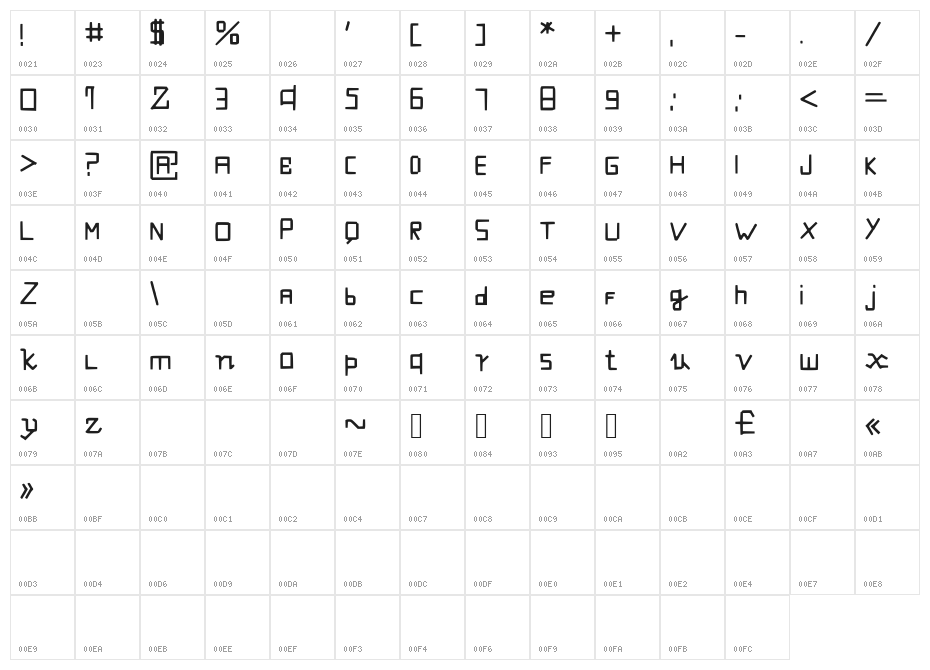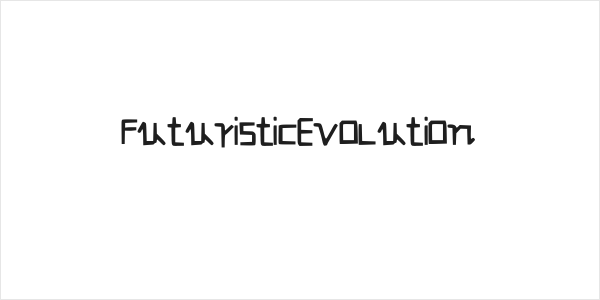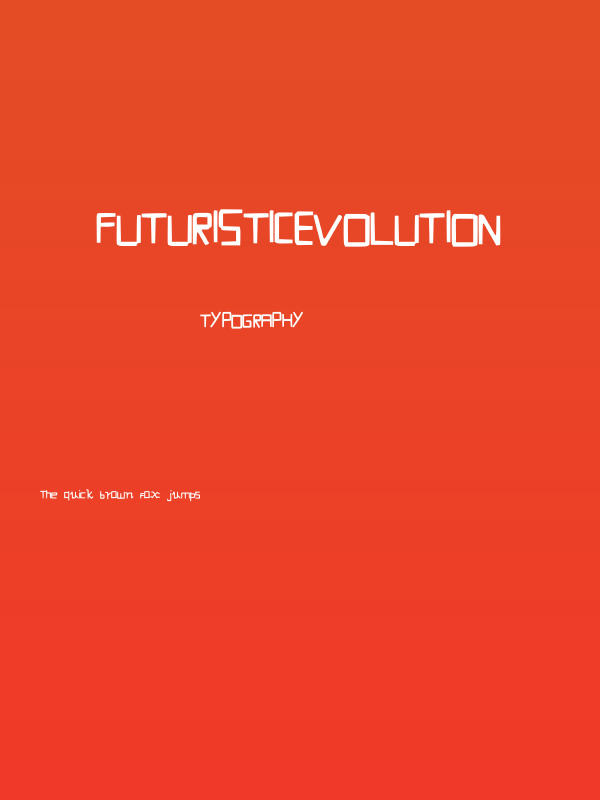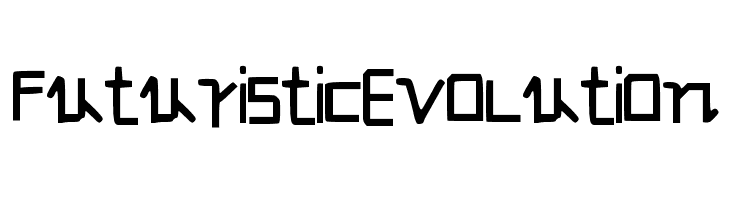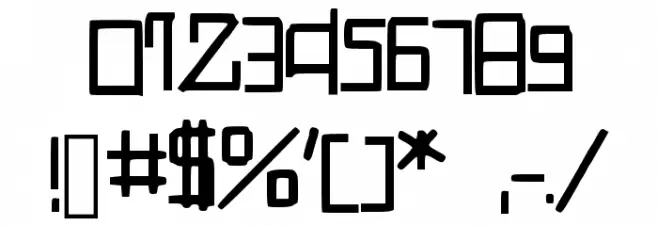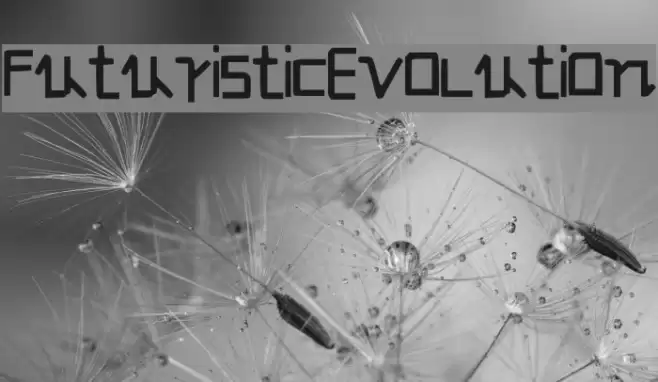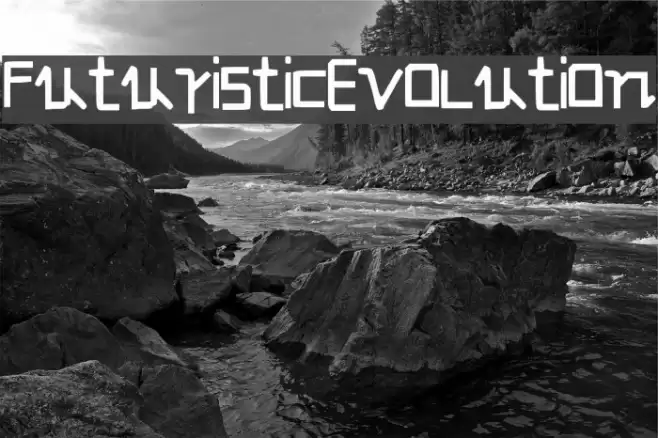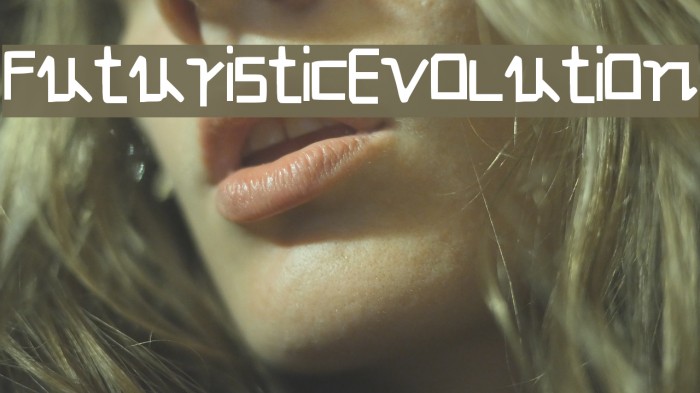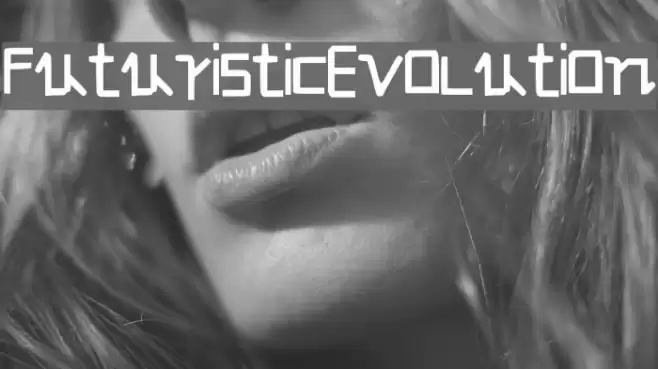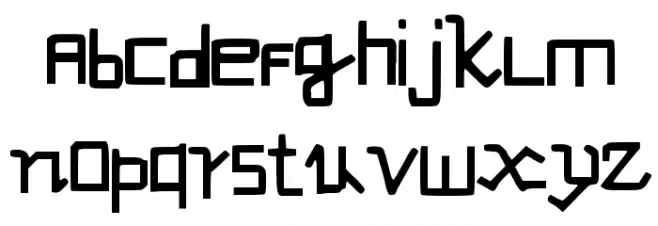
FuturisticEvolution Font
✎ Distorted Eroded
| Vorgeschlagene Projekte | Ideal for tech-related branding, sci-fi movie posters, video game titles, and futuristic-themed websites. |